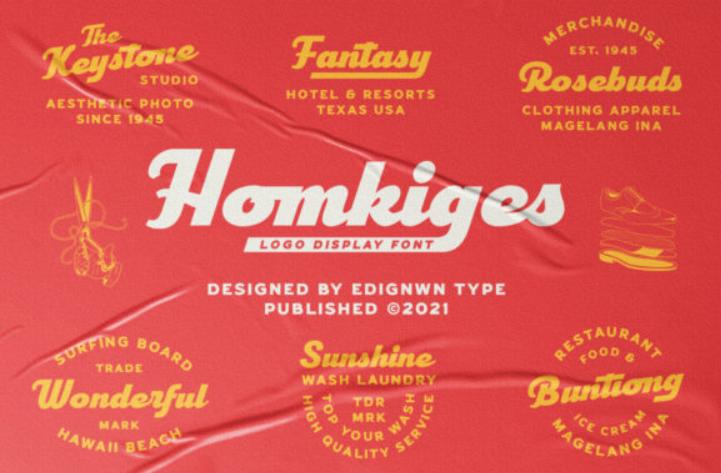
[Creativefabrica] Homkiges Font (Edignwn Type)
Homkiges - это красивая коллекция шрифтов, включая гротеск, скрипт и дингбаты в разных стилях, чтобы удовлетворить любые потребности дизайна. Используйте эту потрясающую коллекцию шрифтов для создания выдающегося дизайна логотипов, плакатов, логотипов, этикеток, упаковки продуктов, футболок или других нестандартных дизайнов. Этот шрифт имеет кодировку PUA, что означает, что вы можете легко получить доступ ко всем глифам и росчеркам!